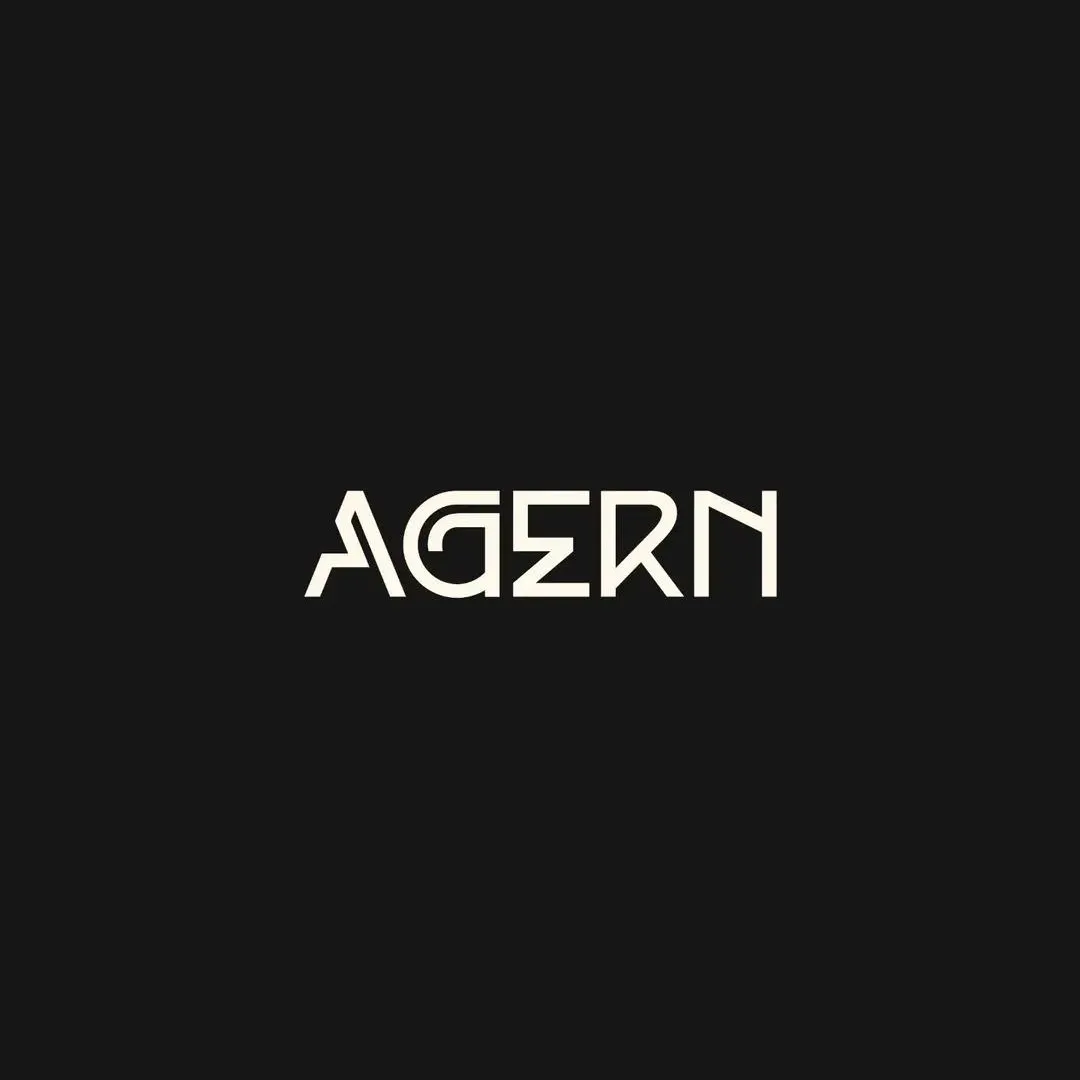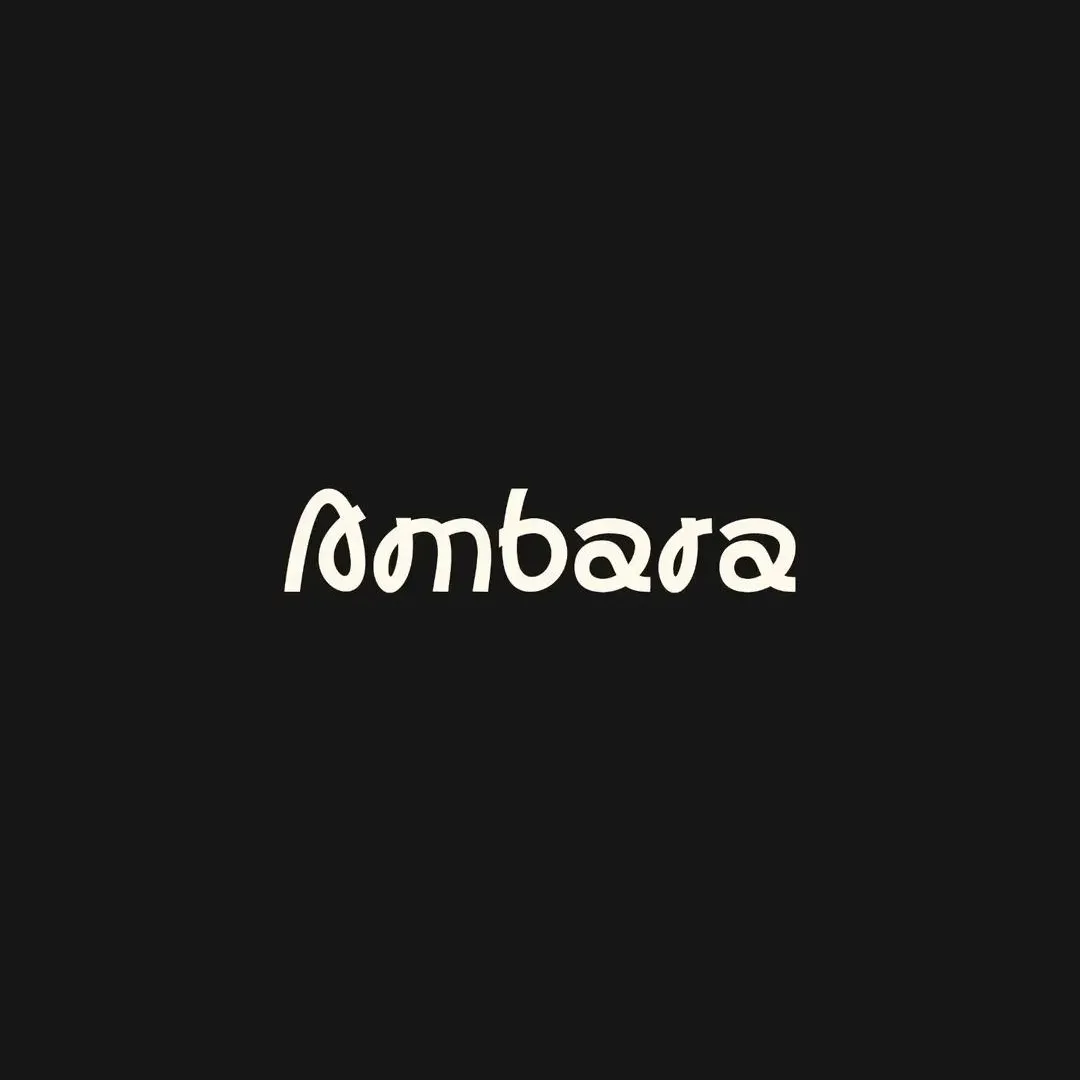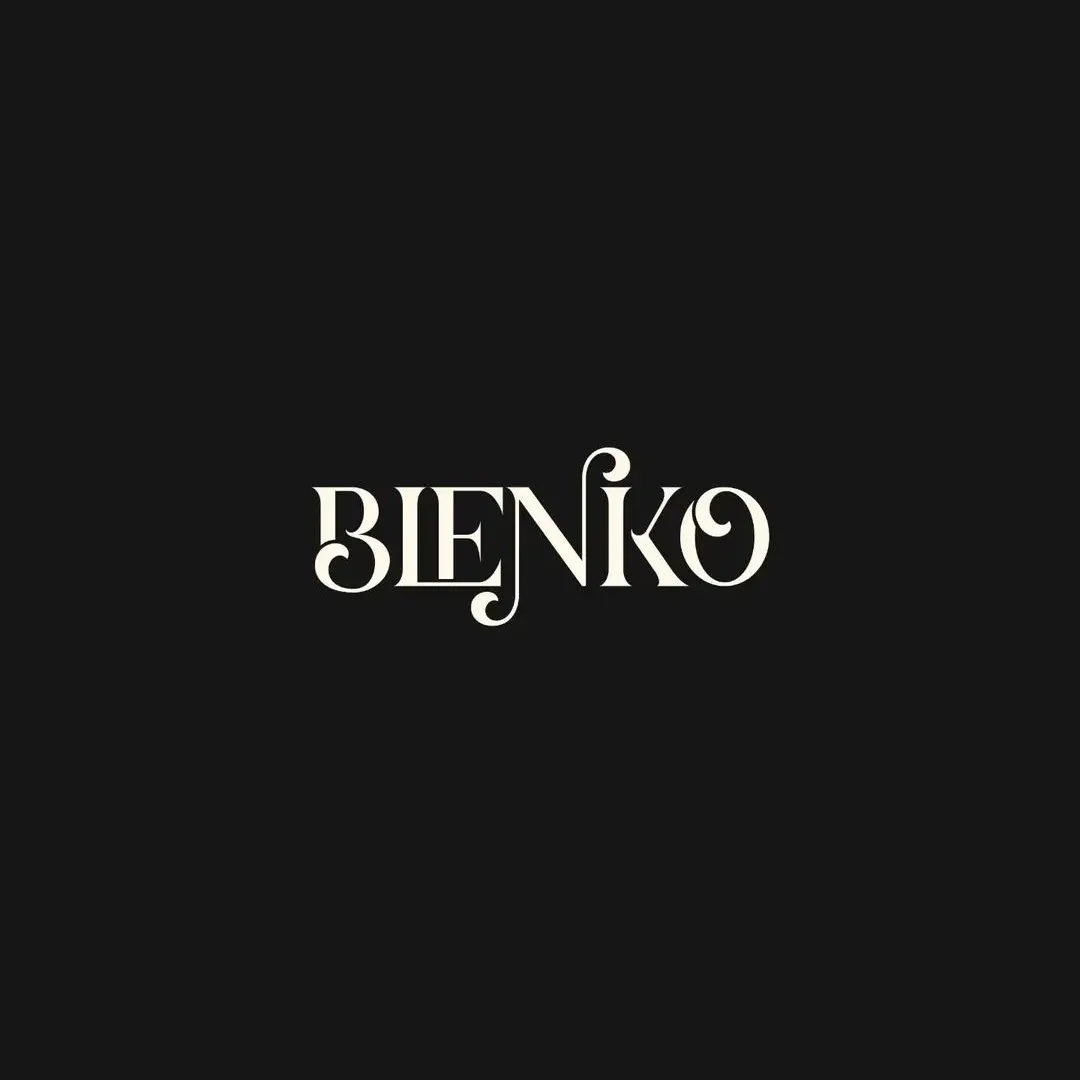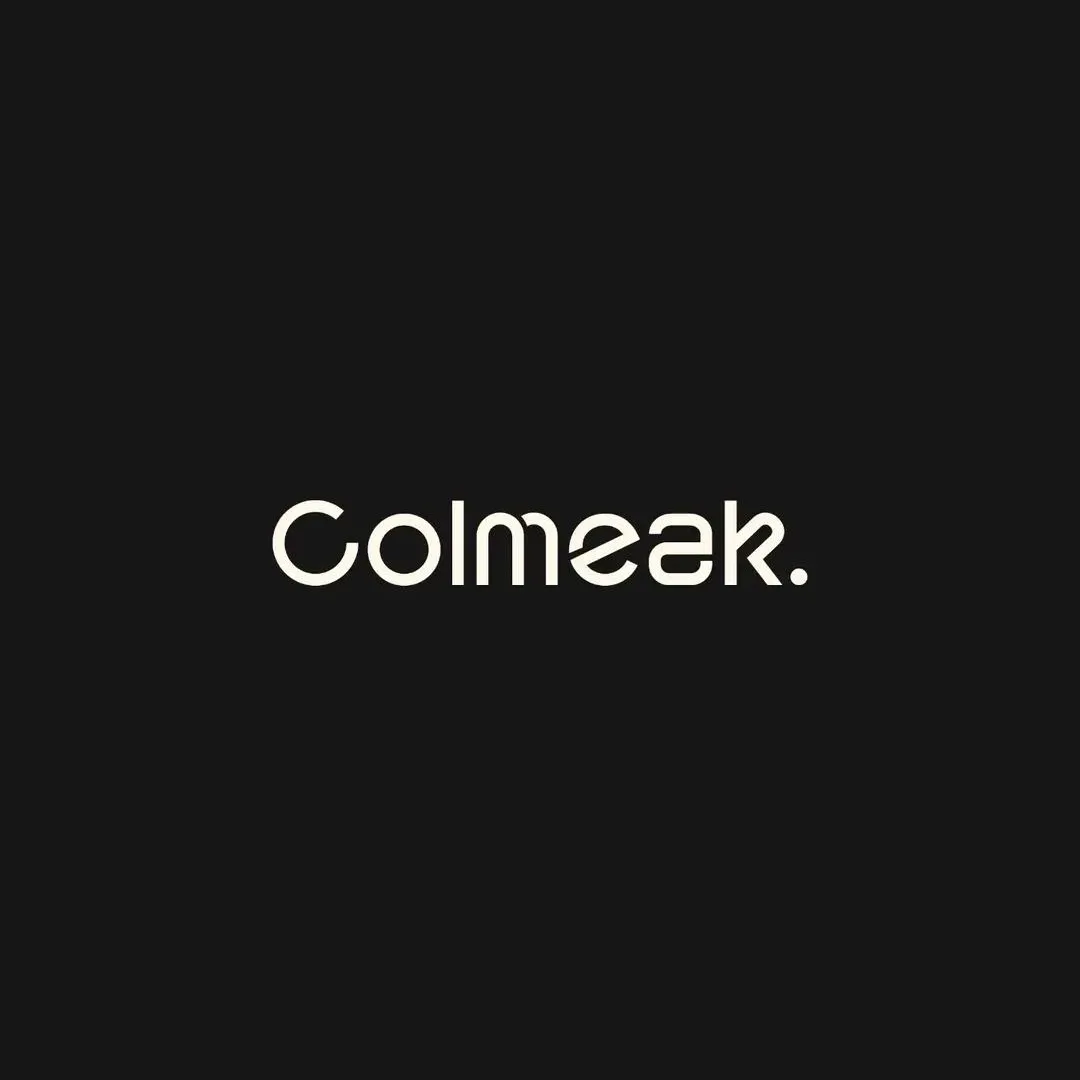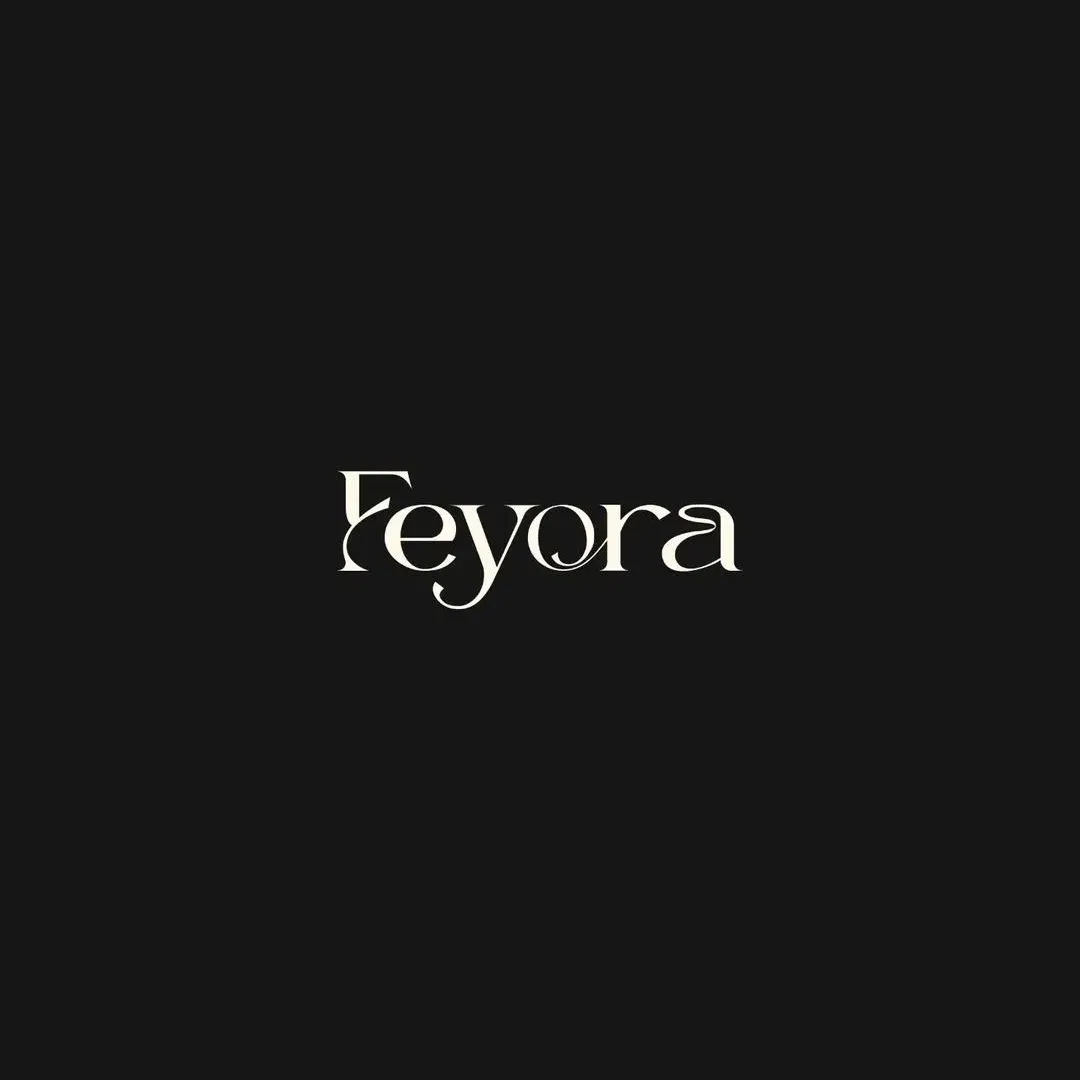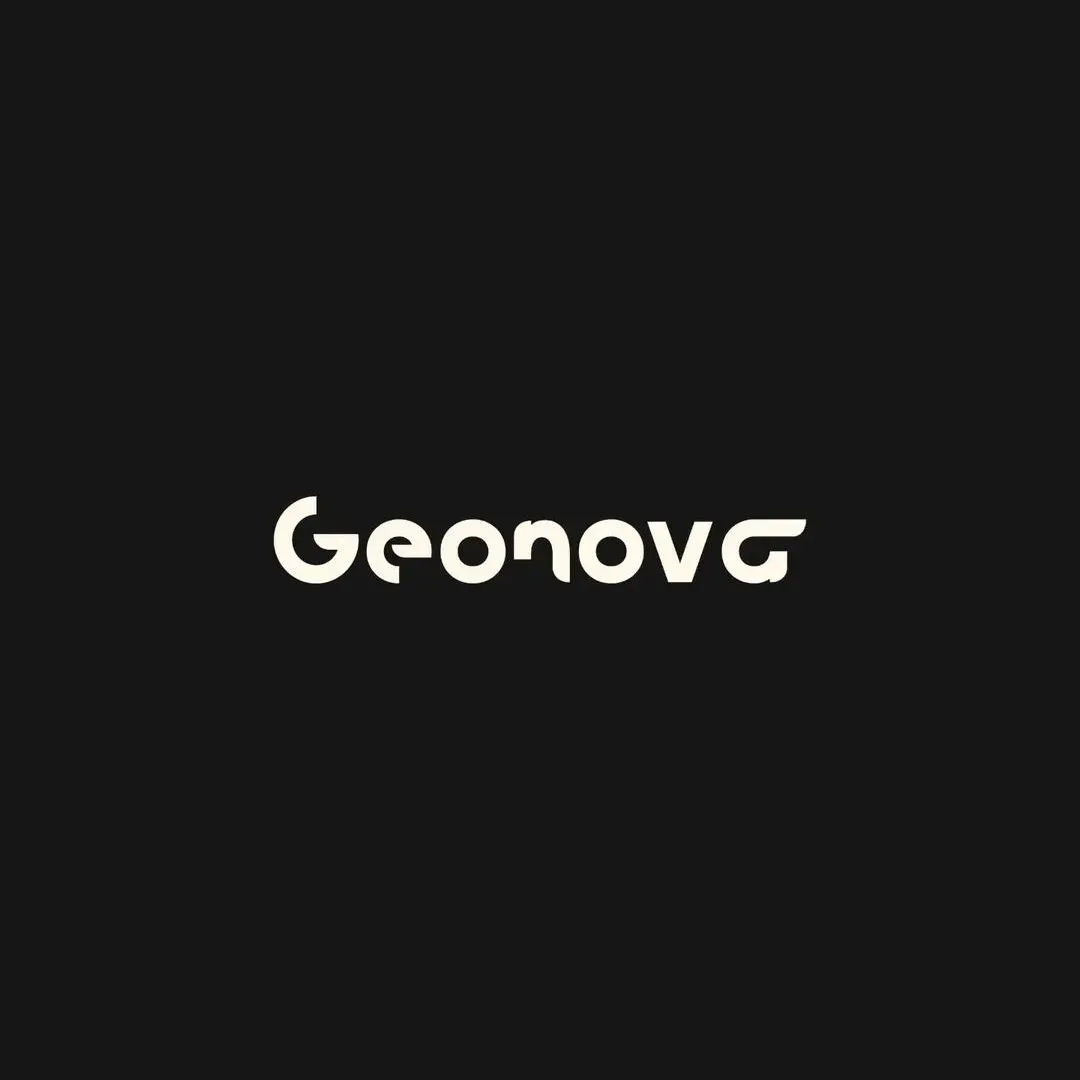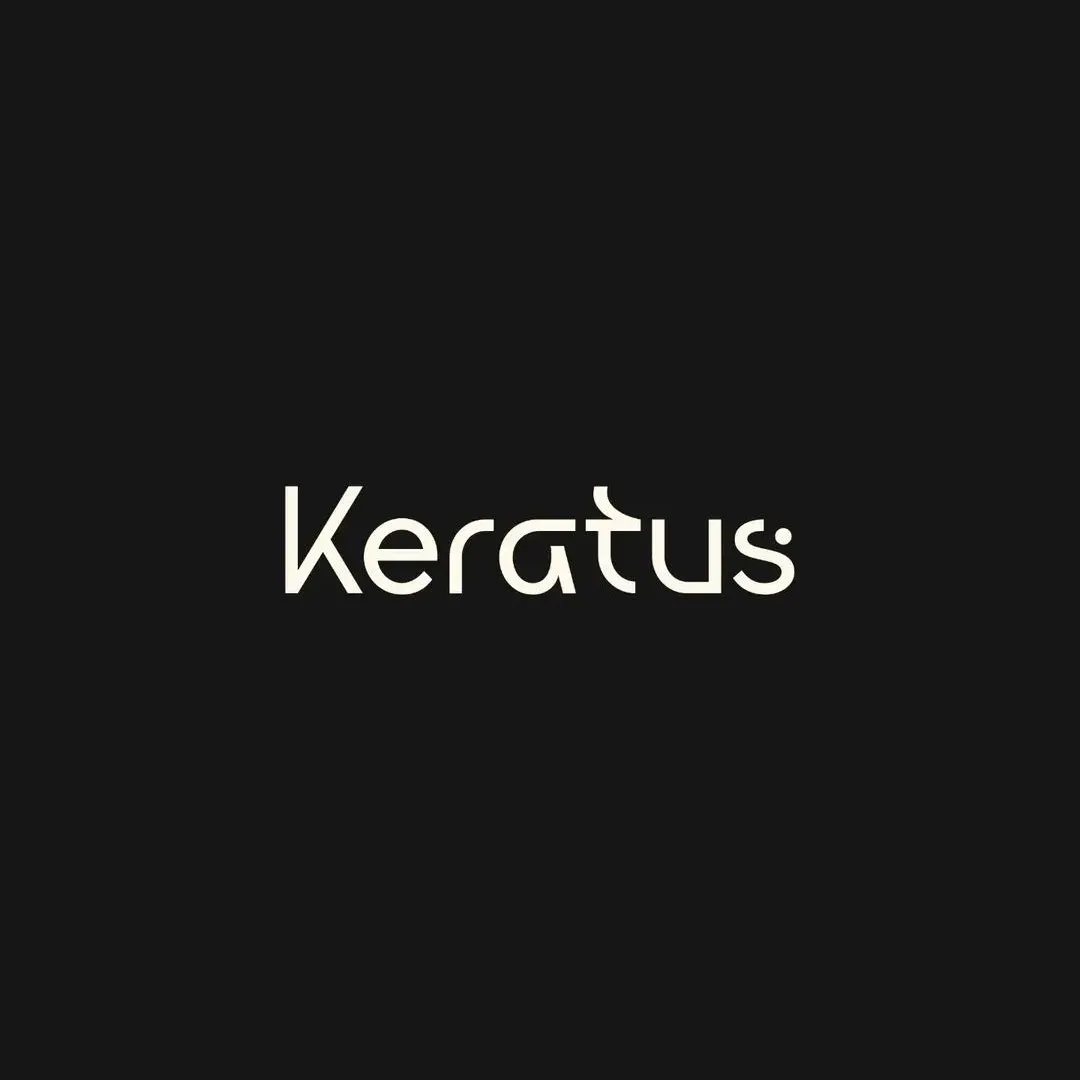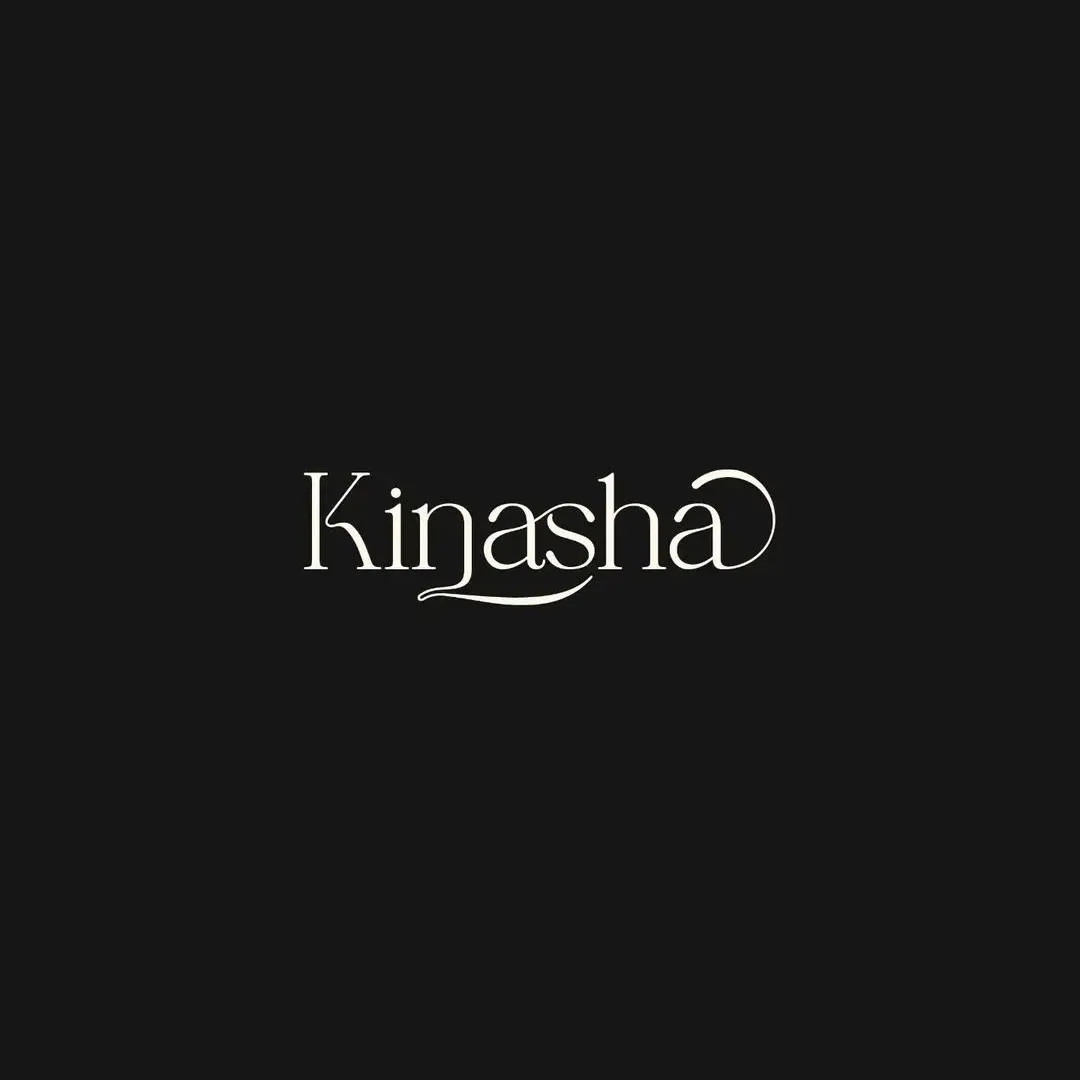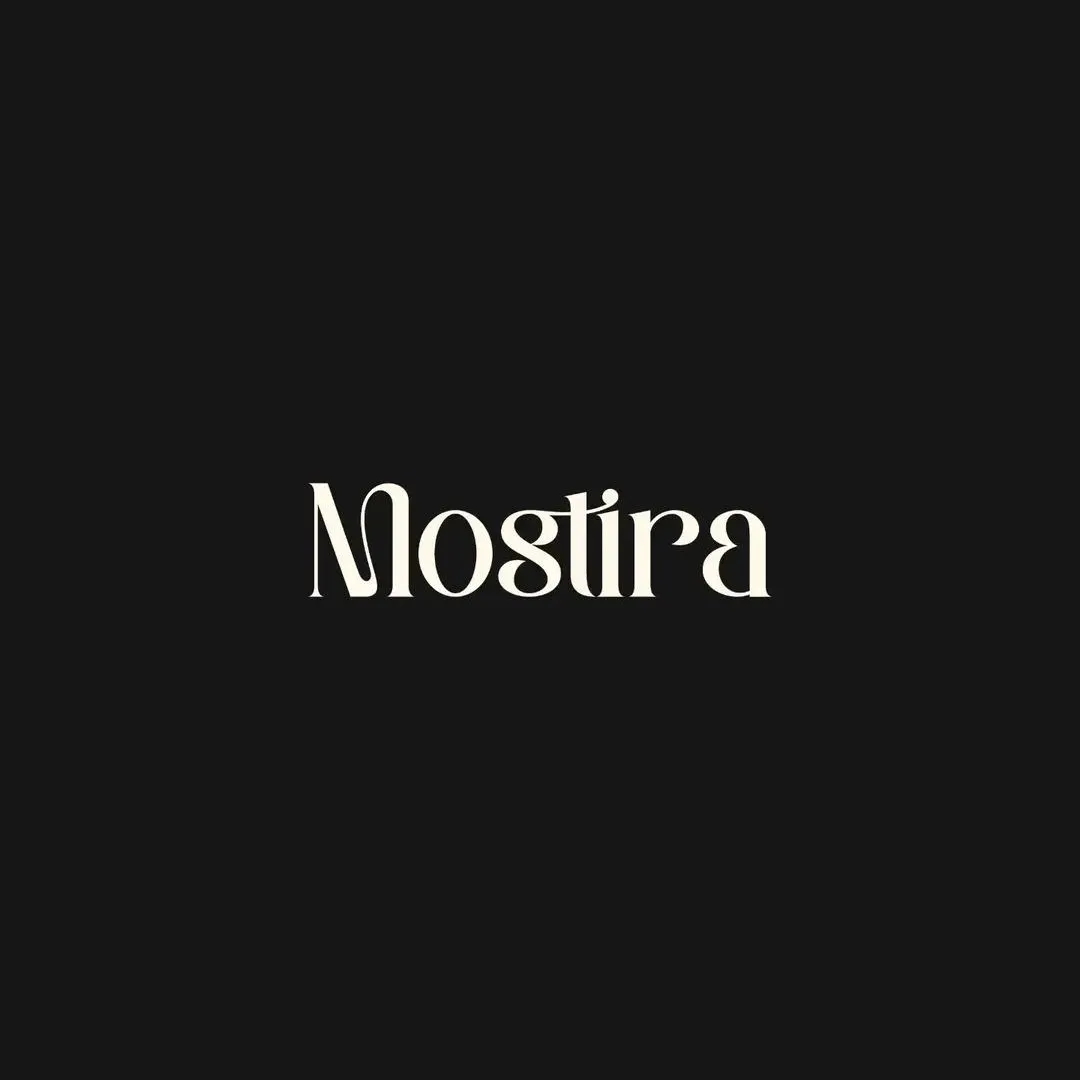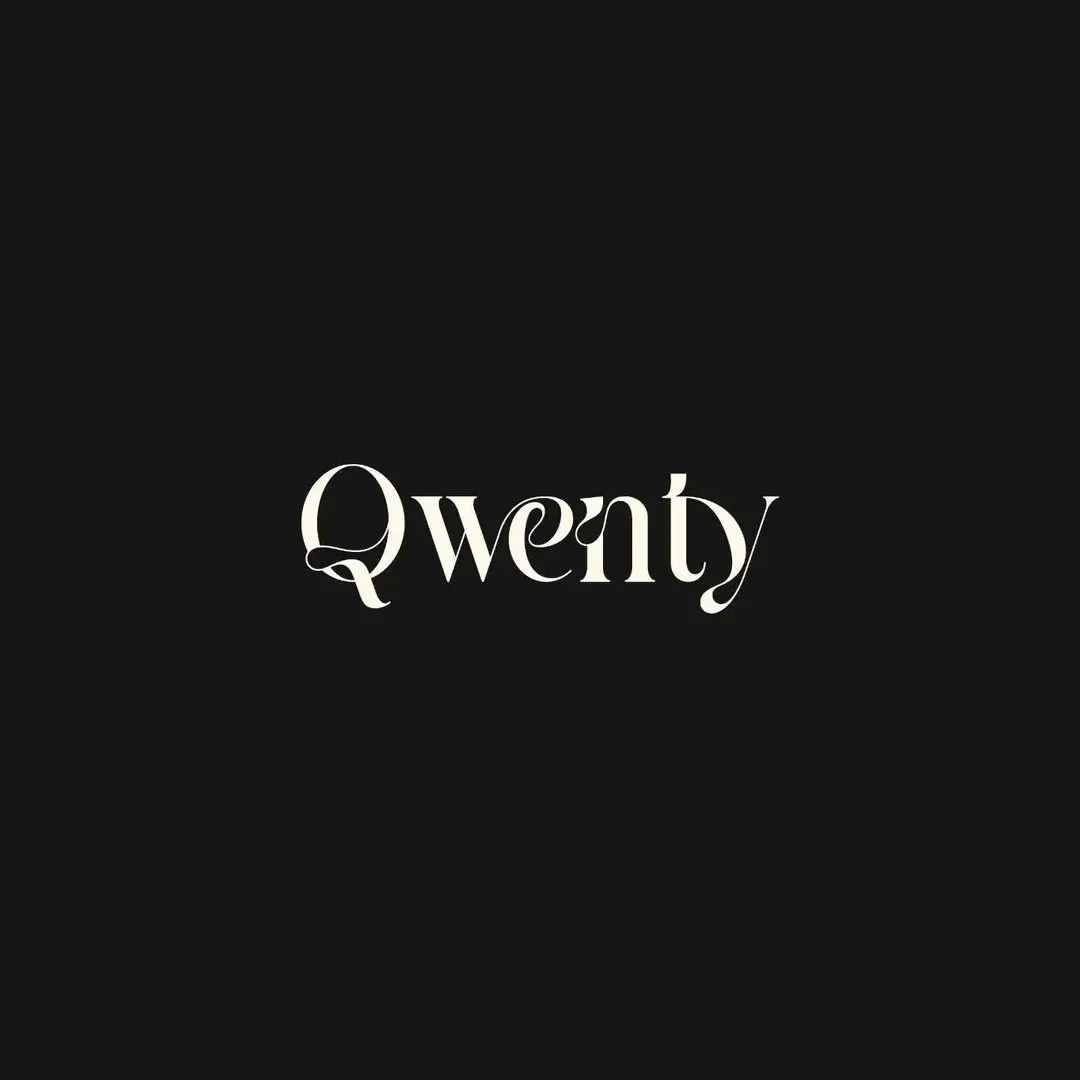
10 Font Terbaik untuk Brand Desainer Seperti Anda
Ini dia 10 font cantik yang bisa kamu pakai secara gratis untuk mendesain logo, kaos, brand identity, pamflet atau brosur untuk media cetak atau digital lainnya.
10 Font Terbaik untuk Brand Desainer Seperti Anda
Bagi seorang desainer, koleksi font ini sangat menarik dan memiliki karakter yang kuat. Masing-masing memiliki “jiwa” yang berbeda. Mari kita bedah satu per satu dari kacamata desain.
Feel, Fungsi dan Rekomendasi Pemakaian.
Kita akan membahas “feel”, fungsionalitas, dan rekomendasi pemakaian untuk setiap font dalam koleksi ini:
1. Font “Kinasha”
Kinasha
• Rasa/Feel: Elegan, mewah, feminin, dan artistik. Font ini memberikan kesan tulisan tangan kaligrafi yang sangat halus dan personal. Ada sentuhan klasik namun tetap terasa modern.
• Fungsionalitas: Ini adalah display font murni. Sangat kuat untuk judul atau logo, namun akan sangat sulit dibaca jika digunakan sebagai teks isi (body text) dalam ukuran kecil. Detail lengkungannya membutuhkan ruang agar bisa terlihat menonjol.
• Rekomendasi Pemakaian: Sangat cocok untuk brand fashion mewah, kosmetik, undangan pernikahan, logo fotografer, butik, atau restoran fine dining.
2. Font “AGERN”
Agern
• Rasa/Feel: Futuristik, teknologi, tegas, dan maskulin. Desainnya sangat geometris dan terstruktur, memberikan kesan kokoh, modern, dan sedikit edgy. Penggunaan huruf Yunani Sigma (Σ) sebagai ‘E’ memperkuat nuansa unik dan teknis.
• Fungsionalitas: Jelas bukan untuk teks panjang. Ini adalah font untuk identitas yang kuat. Fungsinya lebih sebagai elemen grafis daripada alat baca. Sangat efektif untuk menarik perhatian.
• Rekomendasi Pemakaian: Brand teknologi, perusahaan game, produk olahraga, label musik elektronik, arsitektur modern, atau brand otomotif.
3. Font “Bienko”
Bienko
• Rasa/Feel: Ornate (penuh hiasan), vintage, dan misterius. Font ini punya nuansa klasik yang kental, seperti dari era Art Nouveau atau bahkan sedikit sentuhan gothic. Terlihat sangat premium dan eksklusif.
• Fungsionalitas: Sama seperti sebelumnya, ini adalah display font yang kuat. Karena detailnya yang rumit, font ini harus digunakan dalam ukuran besar agar keindahannya tidak hilang.
• Rekomendasi Pemakaian: Merek minuman beralkohol premium (seperti whiskey atau gin), brand cerutu, penjahit busana pria (bespoke tailor), sampul buku fantasi, atau bar dengan konsep speakeasy.
4. Font “Feyora”
Feyora
• Rasa/Feel: Romantis, lembut, alami, dan cantik. Aliran hurufnya sangat organik dan mengalir. Memberikan kesan yang menenangkan dan indah dipandang.
• Fungsionalitas: Sangat ideal untuk wordmark (logo berbasis teks). Karakternya yang sangat khas membuatnya mudah diingat. Kurang fleksibel untuk penggunaan lain selain sebagai identitas utama.
• Rekomendasi Pemakaian: Brand produk kecantikan atau perawatan kulit (skincare), toko bunga, perencana pernikahan (wedding planner), merek pakaian dalam wanita (lingerie), atau patisserie.
5. Font “Ambara”
Ambara
• Rasa/Feel: Eksotis, ramah, santai, dan organik. Bentuk hurufnya unik, seolah terinspirasi dari aksara non-Latin, memberikan nuansa budaya dan kehangatan. Sangat bersahabat dan tidak kaku.
• Fungsionalitas: Cukup baik sebagai logo atau judul. Mungkin masih bisa terbaca untuk sub-judul pendek, tapi tidak untuk paragraf. Keunikannya adalah kekuatan utamanya.
• Rekomendasi Pemakaian: Agensi perjalanan (travel), studio yoga, produk kesehatan dan kebugaran (wellness), merek makanan organik, atau kafe dengan tema bohemian.
6. Font “Keratus”
Keratus
• Rasa/Feel: Modern, minimalis, teknis, dan cerdas. Ini adalah jenis font sans-serif yang bersih tapi punya karakter unik pada beberapa hurufnya (seperti ‘a’ dan ‘u’). Memberi kesan presisi dan inovatif.
• Fungsionalitas: Cukup serbaguna. Selain bagus untuk logo, font ini juga masih sangat terbaca untuk judul dan sub-judul di pamflet atau website. Legibilitasnya cukup tinggi.
• Rekomendasi Pemakaian: Perusahaan teknologi, software, agensi digital, firma arsitektur, merek furnitur modern, atau perusahaan riset.
7. Font “Geonova”
Geonova
• Rasa/Feel: Ceria, modern-retro, tebal, dan bersahabat. Bentuknya yang bulat dan lebar memberikan kesan yang menyenangkan dan mudah didekati. Ada nuansa desain tahun 70-an yang dibalut gaya modern.
• Fungsionalitas: Sangat berdampak sebagai logo atau headline besar. Karena lebarnya, font ini memakan banyak ruang, jadi kurang efisien untuk teks yang padat.
• Rekomendasi Pemakaian: Agensi kreatif, media hiburan, merek mainan anak-anak, produk minuman atau makanan ringan yang menyasar kaum muda.
8. Font “Mostira”
Mostira
• Rasa/Feel: Klasik, berwibawa, terpercaya, dan premium. Ini adalah font serif dengan kontras tebal-tipis yang seimbang, memberikan kesan mapan dan berkualitas tinggi tanpa terlalu banyak hiasan.
• Fungsionalitas: Pilihan yang sangat baik untuk identitas merek (brand identity) yang ingin menonjolkan warisan dan keandalan. Merupakan display font yang legibilitasnya masih sangat baik.
• Rekomendasi Pemakaian: Firma hukum, institusi keuangan, real estate mewah, penerbit buku, atau merek fashion klasik.
9. Font “Colmeak.”
Colmeak
• Rasa/Feel: Minimalis, bersih, ramah, dan modern. Ini adalah font sans-serif rounded yang sangat versatile. Penggunaan titik di akhir kata memberinya sentuhan final yang tegas. Kesannya sangat kekinian.
• Fungsionalitas: Sangat fungsional. Bisa dipakai untuk hampir semua hal: logo, pamflet, kaos, desain UI/UX aplikasi, hingga teks isi. Sangat mudah dibaca dalam berbagai ukuran.
• Rekomendasi Pemakaian: Hampir semua brand modern. Startup, kedai kopi, merek pakaian kasual, konsultan, studio desain. Ini adalah pilihan yang aman namun tetap bergaya.
10. Font “Qweaty”
Qweaty
• Rasa/Feel: Chic, modis, percaya diri, dan sangat bergaya. Termasuk dalam kategori font Didone yang punya kontras sangat tinggi antara garis tebal dan tipis. Lengkungan pada huruf ‘Q’ menjadi pusat perhatian yang mewah.
• Fungsionalitas: Murni untuk display dan branding. Detail garis tipisnya akan hilang jika digunakan dalam ukuran kecil. Sangat sempurna untuk sebuah masthead atau logo utama.
• Rekomendasi Pemakaian: Majalah mode, butik retail, salon kecantikan kelas atas, personal branding untuk influencer atau desainer, atau blog gaya hidup.
Tempat Download Font-font Unik.
Untuk medapatkan font-font ini kamu bisa mencarinya di:
1. Google Fonts:: - Pilihan terbaik untuk font gratis berkualitas tinggi dengan lisensi komersial.
2. Adobe Fonts:: - Jika Anda pelanggan Adobe Creative Cloud, Anda memiliki akses ke ribuan font premium.
3. Creative Market: - Tempat populer bagi desainer independen untuk menjual font. Anda kemungkinan besar akan menemukan font-font bergaya display seperti di atas di sini.
4. Envato Elements:: - Layanan langganan dengan ribuan font dan aset desain lainnya.
5. Behance dan Dribbble: Seringkali desainer font memamerkan karya mereka di sini dan menyertakan tautan untuk membeli atau mengunduhnya.
Penting: Perhatikan Lisensi Font Setelah Anda menemukan fontnya, hal terpenting yang harus dilakukan adalah memeriksa lisensinya.
• Lisensi Personal (Personal Use): Hanya boleh digunakan untuk proyek pribadi yang tidak menghasilkan uang (misalnya, tugas kuliah, desain untuk media sosial pribadi).
• Lisensi Komersial (Commercial Use): Boleh digunakan untuk proyek yang bertujuan komersial (logo brand, pamflet bisnis, kaos yang dijual, dll.) Font gratis seperti dari Google Fonts biasanya aman untuk penggunaan komersial, tetapi font dari situs seperti Creative Market atau MyFonts harus dibeli untuk mendapatkan lisensi komersialnya. Selalu baca baik-baik ketentuan lisensi sebelum menggunakannya.
Alternatif Gratisan?
Untuk mencari fonts di beberapa situs yang sudah disebutkan di atas, Anda bisa menggunakan kata kunci tertentu. Kata kunci yang bisa digunakan antara lain:
Untuk font seperti Kinasha, Feyora, Mostira, Qwenty, Bienko:
• Elegant Serif
• Luxury Font
• Fashion Serif
• Didone Font
• Font with Ligatures (Font dengan Sambungan)
Untuk font seperti AGERN, Keratus, Geonova:
• Geometric Sans Serif
• Futuristic Font
• Modern Tech Font
• Rounded Sans
Untuk font seperti Ambara, Colmeak:
• Minimalist Sans Serif
• Rounded Font
• Friendly Sans